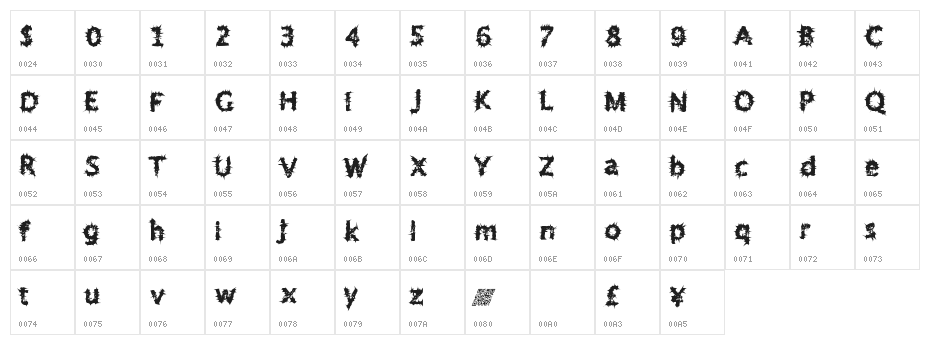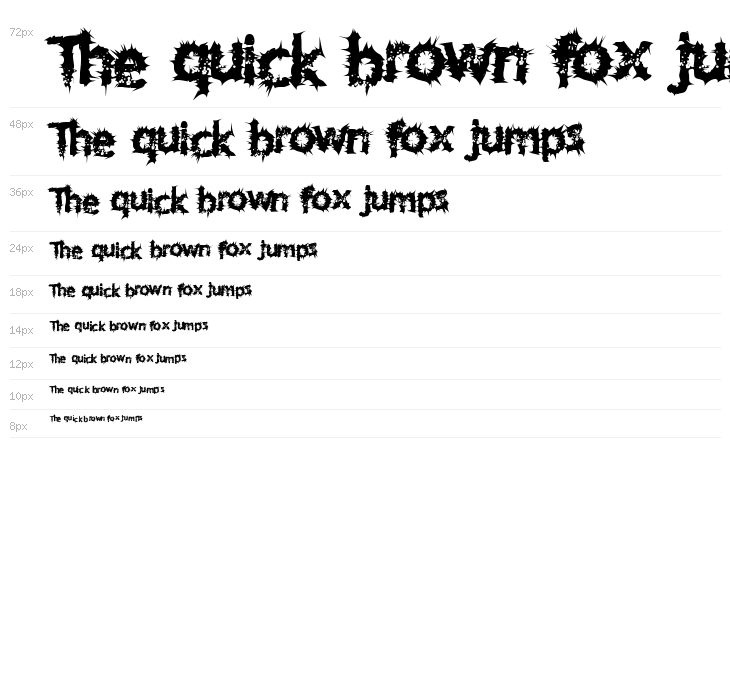
TenDimensional Font
| Vorgeschlagene Projekte | Ideal for horror-themed posters, edgy album covers, or any design needing a bold, unconventional look. |